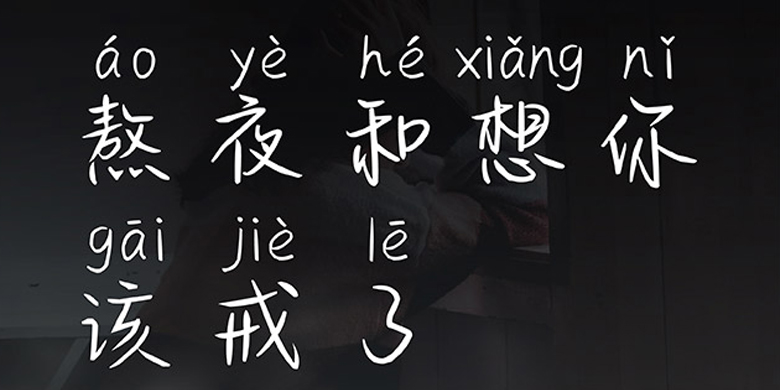
方正手迹-熬夜和想你该戒了
字体品牌: 方正手迹 设计师:宋昱东 字体分类:创意书写 字体属性:精品字 字符集:大陆简体(GB2312-80) 发布时间: 2020
熬夜和想你该戒了是一款拼音体,正文汉字转折多用圆角,结构轻松有趣,搭配英文拼音更显活泼可爱。适用于少年儿童类书刊、综艺影视字幕用字、漫画用字,以及社交网络的个性化用字。